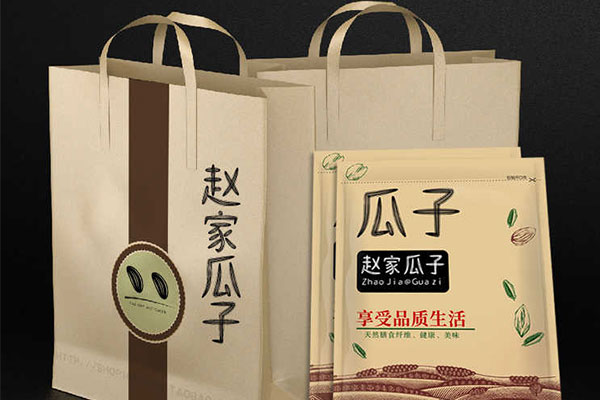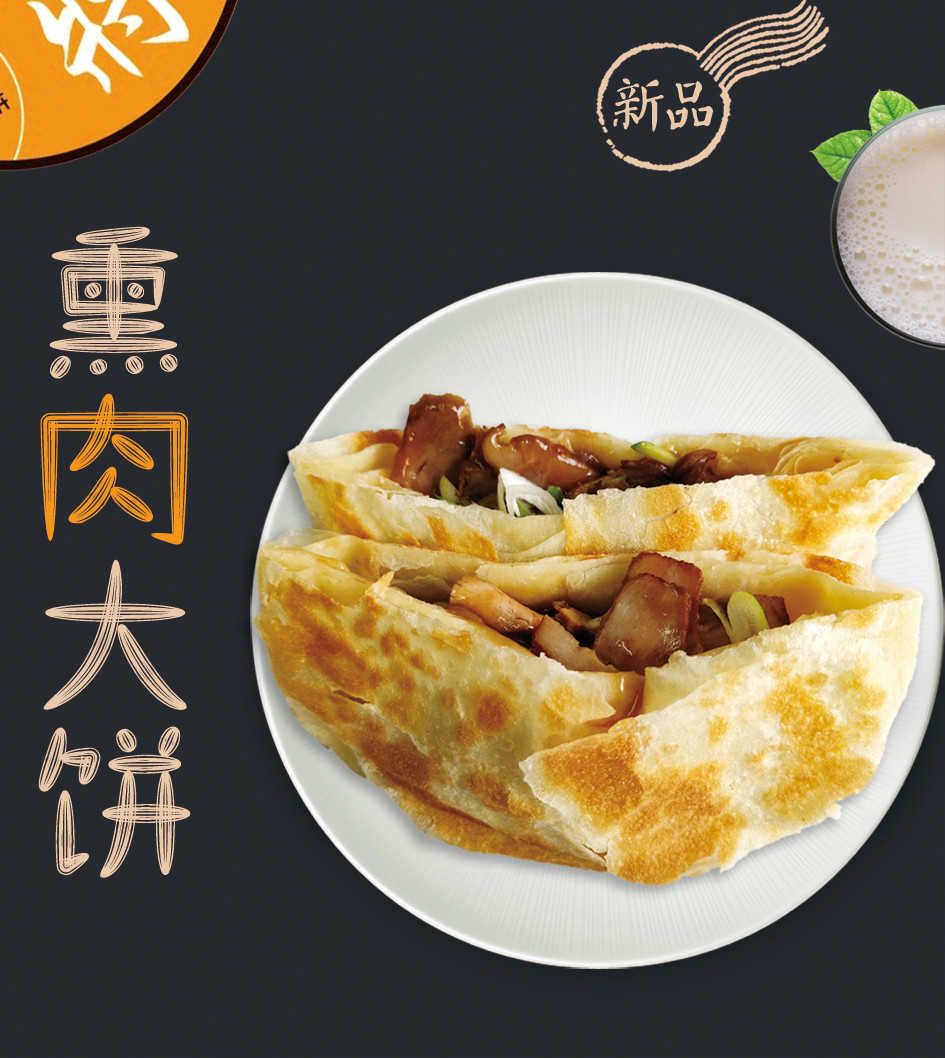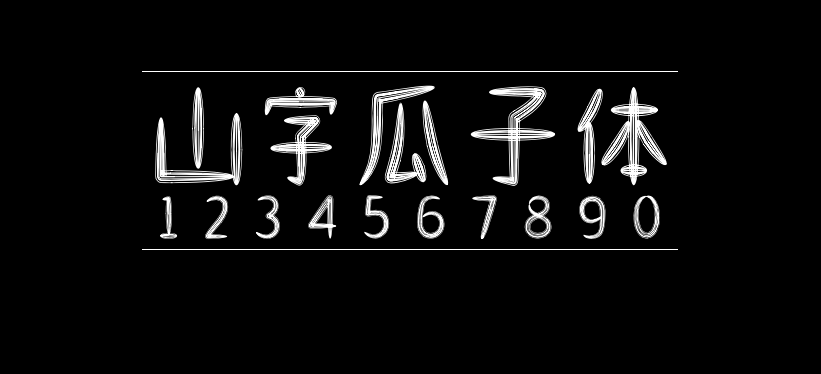
山字瓜子体
山字瓜子体是中国大陆的frank L在图文店期间做的一款字体,免费分享给大家(山字瓜子体,个人和企业商用均免费)。
山字瓜子体包含GB2312规范的6763个常用中文字以及若干英文常用字母和标点符号。由于笔画形似瓜子,故取名瓜子体。也因为所用笔画是常规字库的数倍,字库也比常规简单笔画的字库要大许多。
该字库适合广告设计中需要用到可爱或卡通的字体的时候,适合用大字体来显示,并不适合用小字(如四号等)来显示。
山字瓜子体字体效果预览